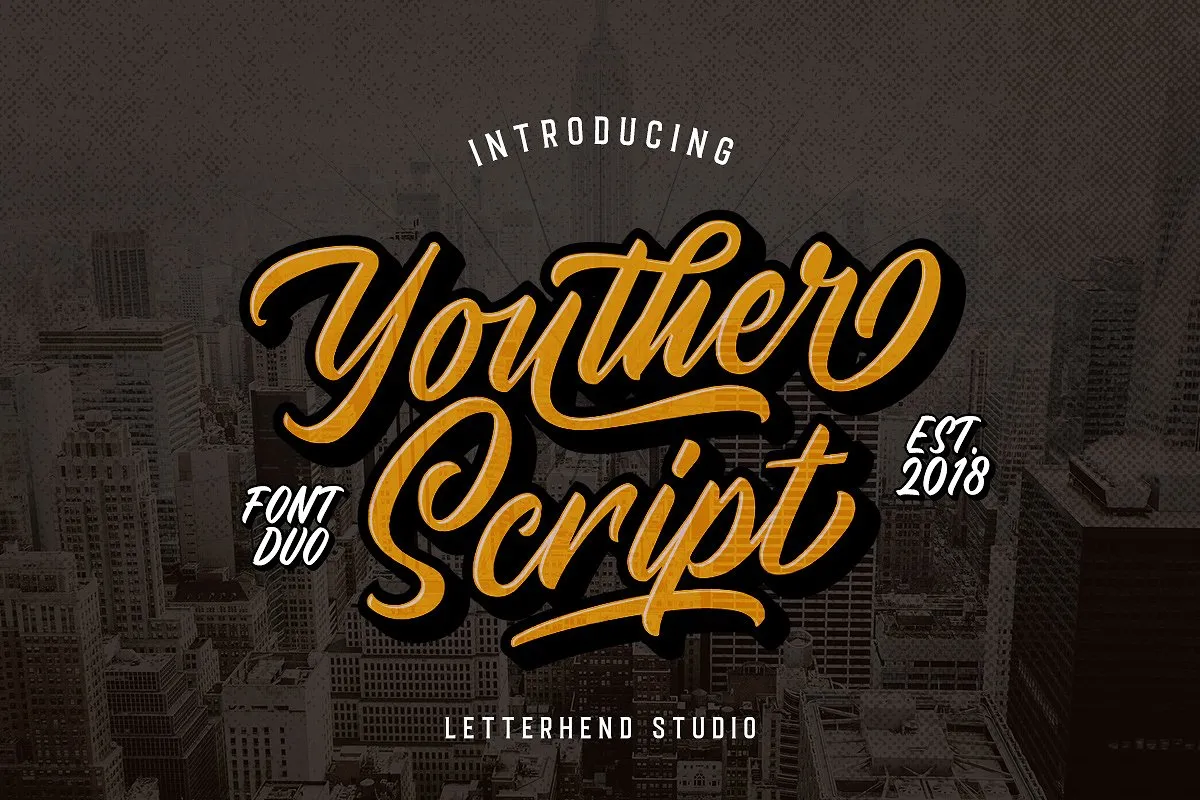
Youther Script Font – Download Grátis
A fonte ‘Youther Script Font’ é uma dupla de fontes feitas com mãos delicadas para produzir uma fonte de alta qualidade, criada pelo designer Letterhend. Este duo de letras estilizadas possui um design sofisticado e multifacetado que permite fazer tipografia elegante sem a necessidade de nenhuma ferramenta adicional ou atalho. Essa família de fontes inclui uma escrita fantástica, além de um tipo em maiúsculas. Vocêther é perfeito para ser utilizado como logomarca, logotipo e etiqueta. Além disso, a ‘Youther Script Font’ oferece muitas características do OpenType, como ligação, alterações estilísticas alternativas, alternativas contextuais, swash, entre outros. Também suporta múltiplas línguas, tornando-a uma escolha versátil para designers e criadores de conteúdo. Vocêther é perfeito para criar designs exuberantes e sofisticados, com um acabamento cuidadosamente refinado que certamente impressionará seu público-alvo.